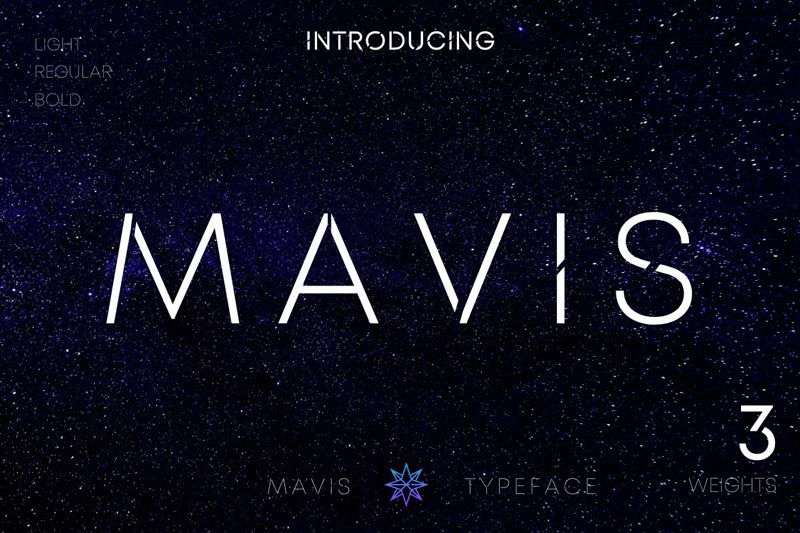
- طراحی حرفه ای فونت با بالاترین کیفیت
- مناسب برای انواع طرح ها و پروژه ها
- نمایش بی نقص تمامی حروف و اعداد بدون مشکل
- نمایش صحیح در سایز و اندازه های گوناگون
Introducing MAVIS SANS FUTURISTIC & SPACE Typeface
MAVIS is a futuristic, space & tech looking font family.
It’s thin and simple, but it’s strong and significant defined by its thin strokes and unique cuts. It is designed for optimal legibility. An all caps sans-serif, MAVIS makes a strong attention grabber for any occasions.
Three weights for very different personalities.
- MAVIS Bold – Thin yet bold and strong!
- MAVIS Light – Delicate, elite & in style.
- MAVIS Regular – The best of the both worlds!
It is great for any branding with futuristic, space & tech theme or any theme for header, logos, video game, magazine film, typography project, book and cover.